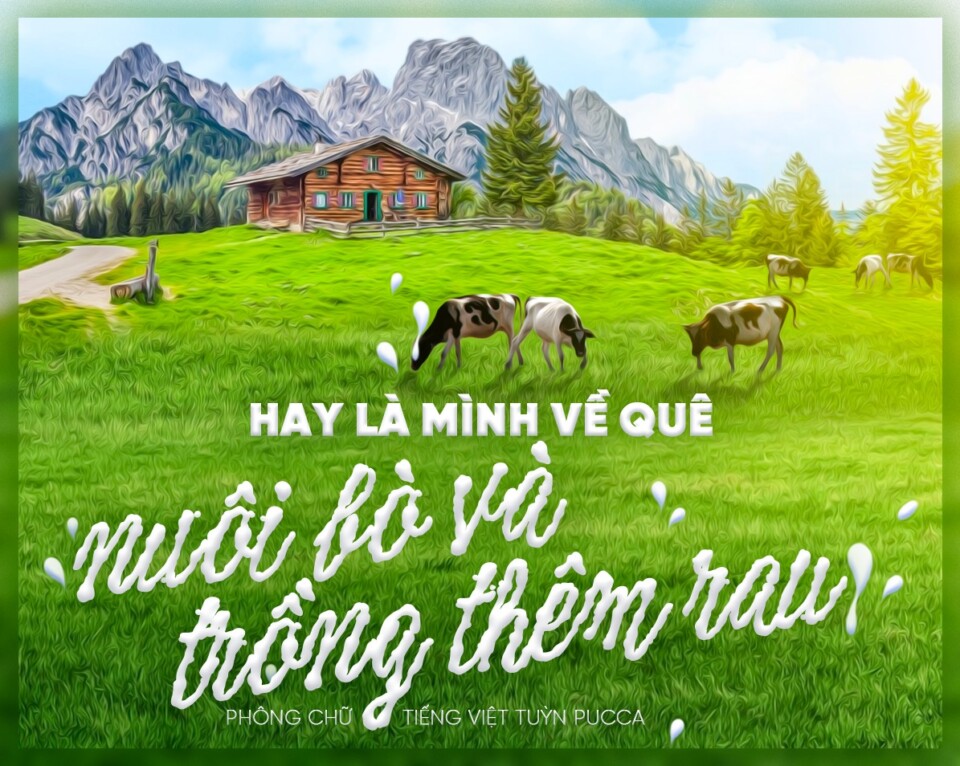
Giới thiệu về bộ Font Việt hóa TP Liquida dành cho thiết kế
Trong thế giới đồ họa hiện đại, việc lựa chọn một Font Miễn Phí chất lượng luôn là ưu tiên hàng đầu của các nhà thiết kế trẻ. Font Việt hóa TP Liquida nổi lên như một hiện tượng nhờ phong cách lỏng lỏng, mềm mại nhưng không kém phần phá cách. Đây là bộ phông chữ lấy cảm hứng từ những đường nét chuyển động của chất lỏng, mang lại cảm giác thị giác cực kỳ ấn tượng cho người xem ngay từ cái nhìn đầu tiên. Đối với các bạn học sinh và sinh viên yêu thích sự sáng tạo, bộ chữ này chính là công cụ đắc lực để biến những bài thuyết trình hay báo cáo trường học trở nên sinh động và chuyên nghiệp hơn bao giờ hết.
Tại sao bạn nên chọn Font Việt hóa TP Liquida?
Đặc điểm nổi bật nhất của Font Việt hóa TP Liquida chính là sự linh hoạt trong ứng dụng. Bộ chữ đã được tối ưu hóa hoàn toàn bảng mã tiếng Việt, giúp người dùng không còn lo lắng về lỗi hiển thị dấu hay khoảng cách chữ không đều. Cấu trúc các ký tự được thiết kế với độ tương phản cao, tạo nên một nhịp điệu riêng biệt cho văn bản. Bạn có thể sử dụng nó cho các tiêu đề lớn trên bìa sách, áp phích sự kiện hoặc thậm chí là thiết kế logo cho câu lạc bộ trường học. Sự kết hợp giữa nét thanh mảnh và những điểm nhấn uốn lượn giúp font chữ này giữ được vẻ thanh lịch mà vẫn đậm chất nghệ thuật.
Để đạt hiệu quả tốt nhất, bạn nên phối hợp Font Việt hóa TP Liquida với các phông chữ không chân (sans-serif) đơn giản để cân bằng thị giác. Hãy sử dụng nó cho các phần tiêu đề chính để tạo điểm nhấn mạnh mẽ. Với sự hỗ trợ tận tình từ cộng đồng thiết kế, việc tải và cài đặt bộ chữ này vô cùng đơn giản trên cả Windows và macOS. Đây thực sự là lựa chọn tuyệt vời để nâng tầm dự án cá nhân của bạn. Đừng bỏ lỡ cơ hội trải nghiệm tại Font Miễn Phí, Font Việt Hóa, Font Việt hóa TP Liquida ngay hôm nay.